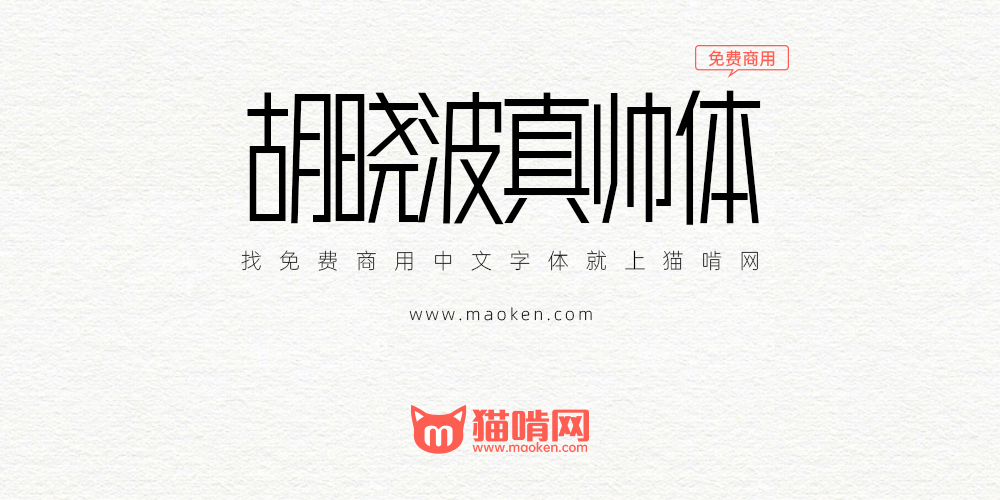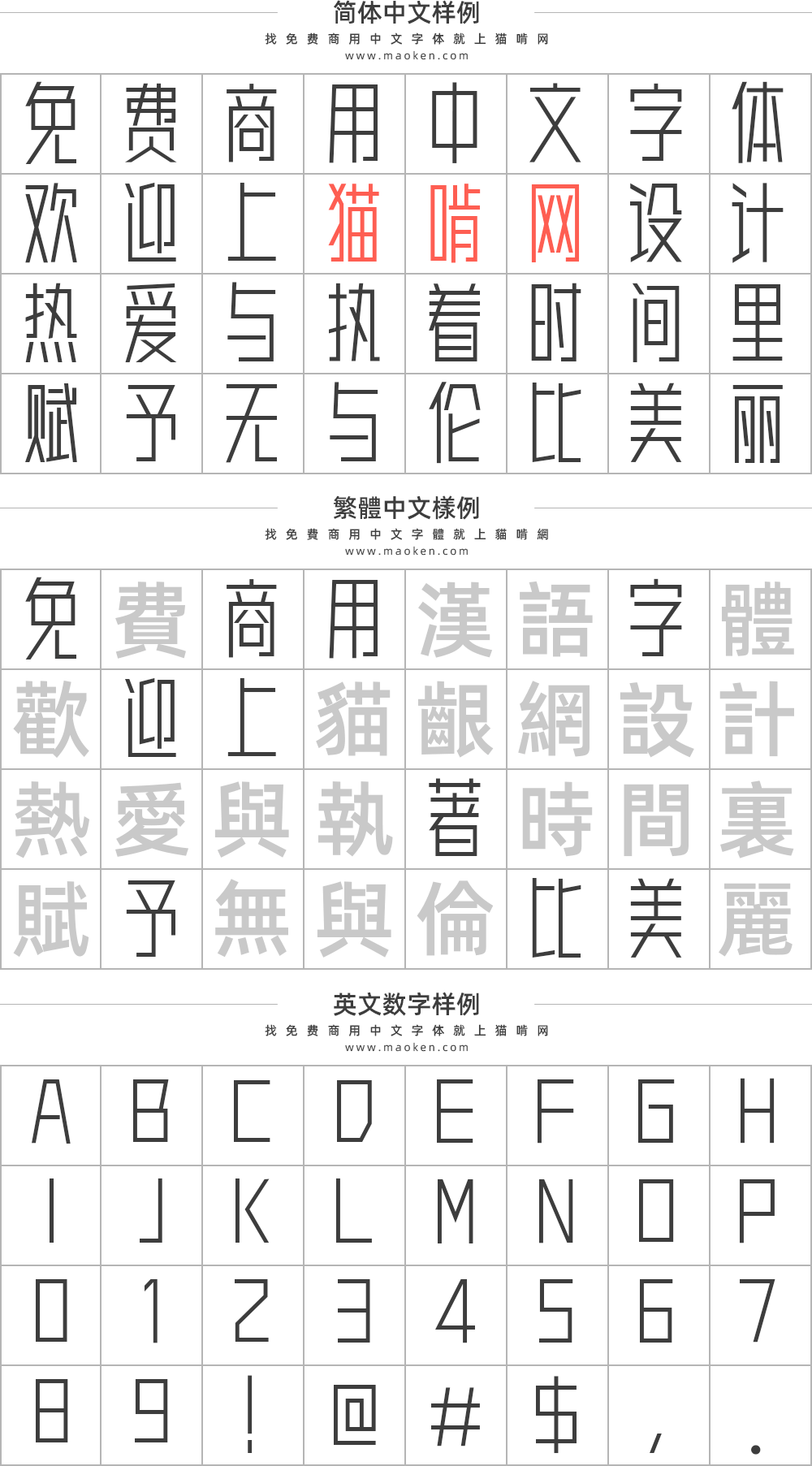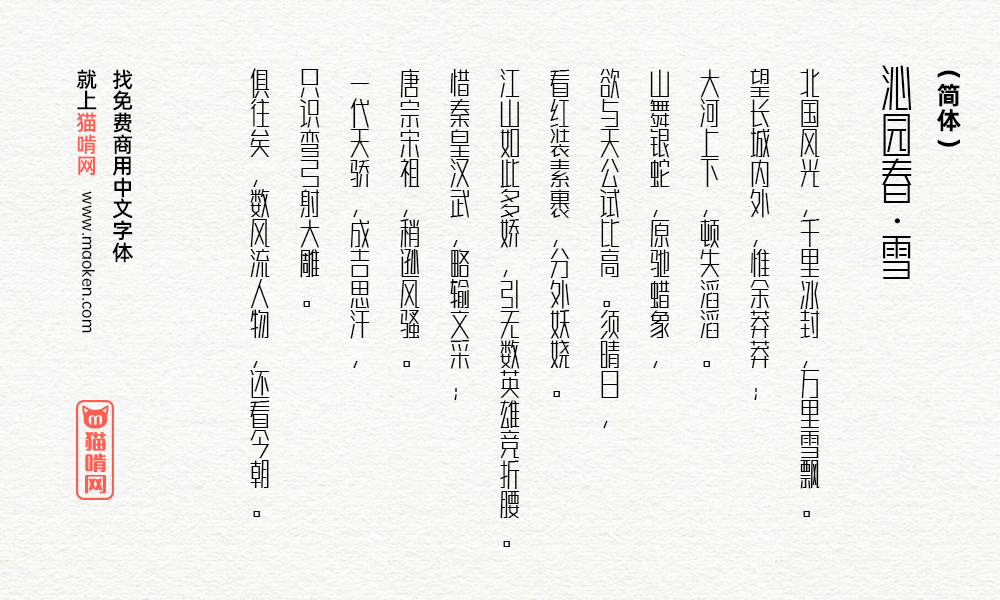
胡晓波真帅体:这个胡晓波是真的超级帅
2019年12月23日,在圣诞节前夕,站酷人气设计师胡晓波在庞门正道公众号上一口气发布了三款可免费商用的中文字体。这三款字体分别是胡晓波真帅体胡晓波骚包体胡晓波男神体,我们来认真看看这三款字,命名非常骚气,完全符合胡晓波的性格。可以连起来看,一句话说完三个字体:一个骚包的真帅男神。
这一款胡晓波真帅体字型重心提高,笔划纤瘦,中宫放大,字型感觉十分高档。十分适合于表现高档,奢华,简约等设计风格。